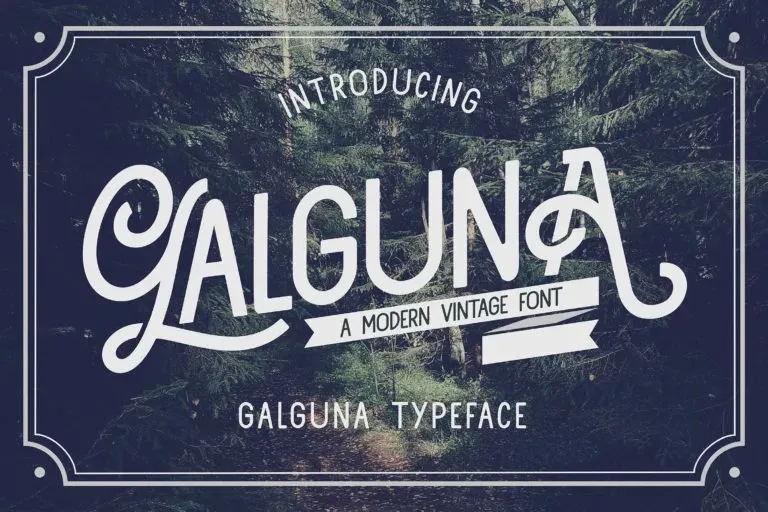
A Galguna Font é uma elegante tipografia sans-serif criada pela Type Factory. Ela traz uma sensação de sofisticação e clareza que a torna irresistível para qualquer público-alvo que a veja. Com seu estilo de letra francesa, essa fonte se destaca na classe dos tipos sem serif, fazendo-a única e memorável. Suas linhas leves e perfeitas combinam perfeitamente com diversos usos práticos, desde cartões de visita até logos ou capas de revistas. Com a Galguna Font, você abrirá caminho para inúmeras possibilidades em qualquer aplicação gráfica. Não importa o uso que você escolha dar à fonte, ela manterá um equilíbrio perfeito entre modernidade e clareza visual, tornando-a uma ótima adição ao seu arsenal de ferramentas de design.